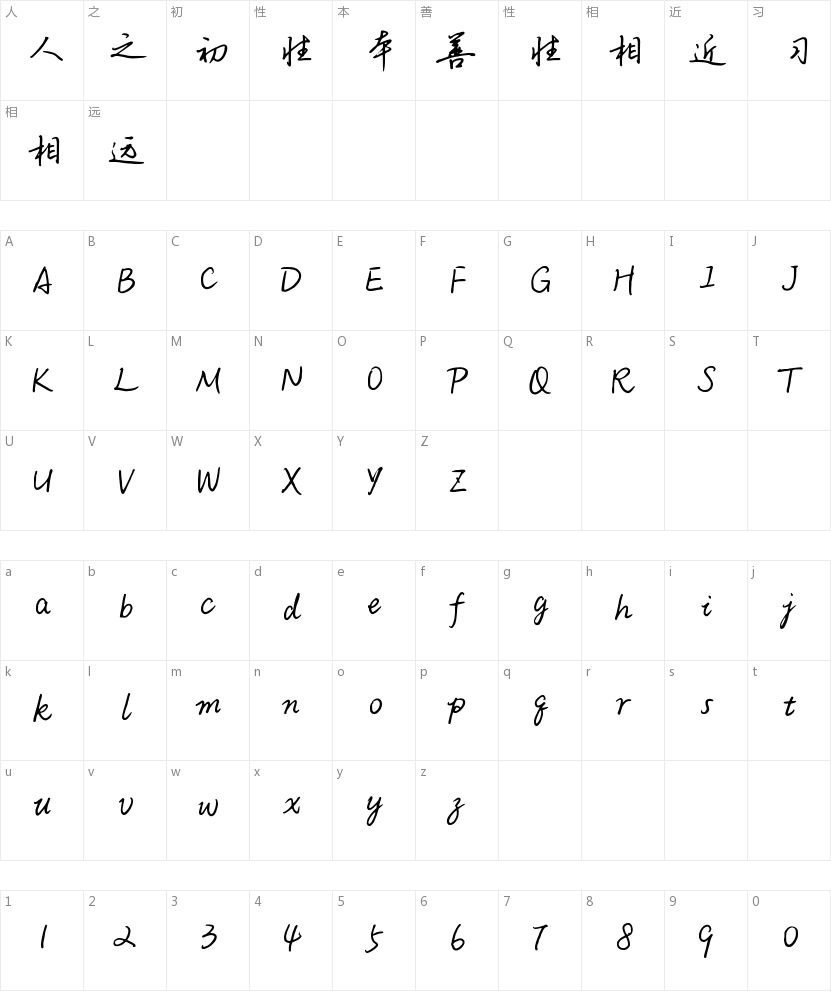
钟齐陈伟勋硬笔行书
? 钟齐陈伟勋硬笔行书是由钟齐陈伟勋先生创作的一种硬笔书法。其特点是笔画清晰,笔势稳健,挥洒自如,结构严谨,笔画比例协调,字体细腻,曲线优美,具有浓郁的汉风,令人赏心悦目。字体以楷书为主,传统楷书为主,更有自创的行书,并结合楷书与行书,形成一种独特的钟齐陈伟勋硬笔行书。
钟齐陈伟勋硬笔行书是一款非常不错的手写艺术字体,具有很好的视觉感,适合于文化类的宣传设计、商业类品牌的广告和产品包装设计以及个性化文字排版等较多场景。